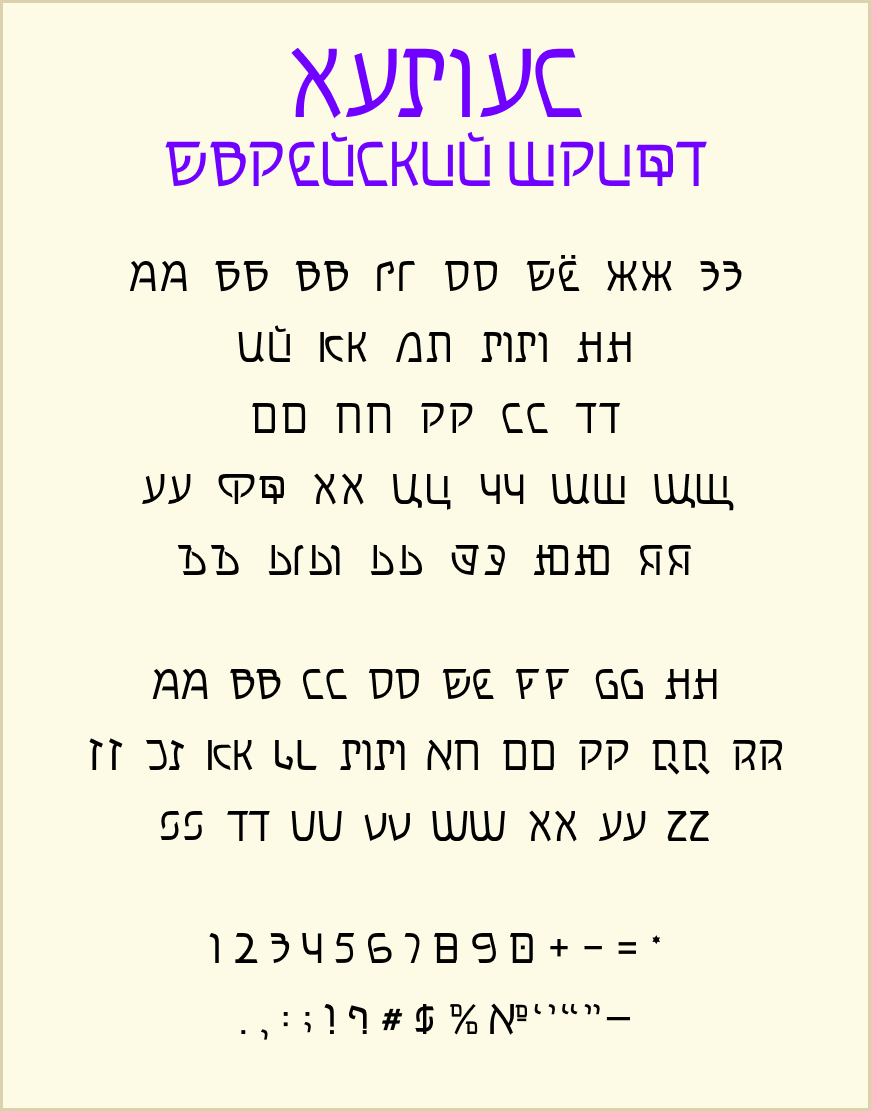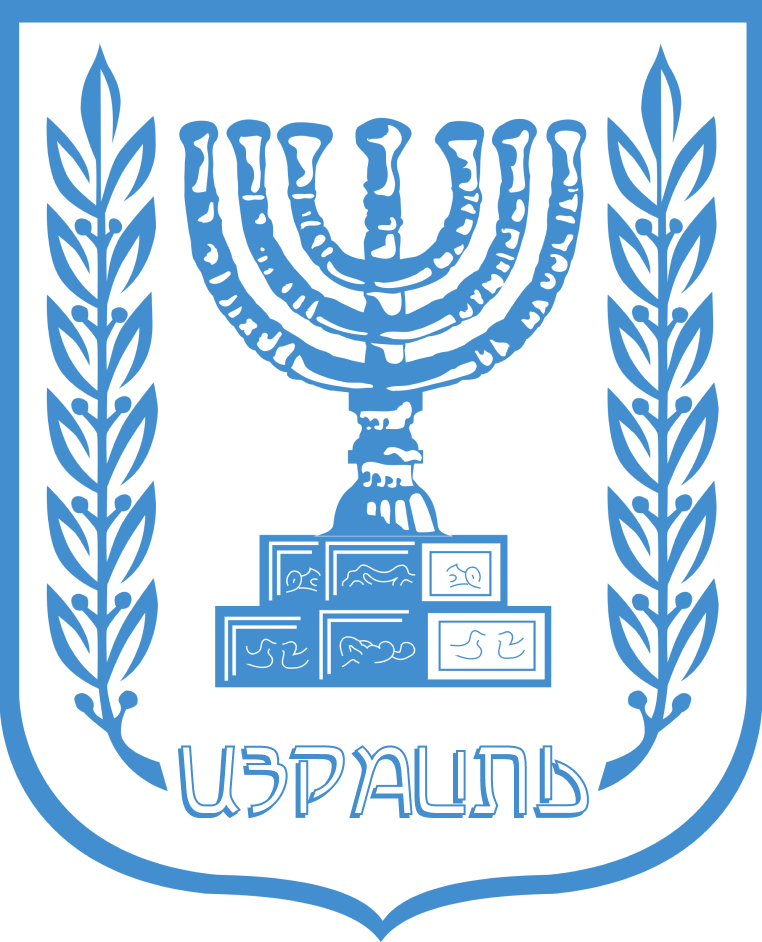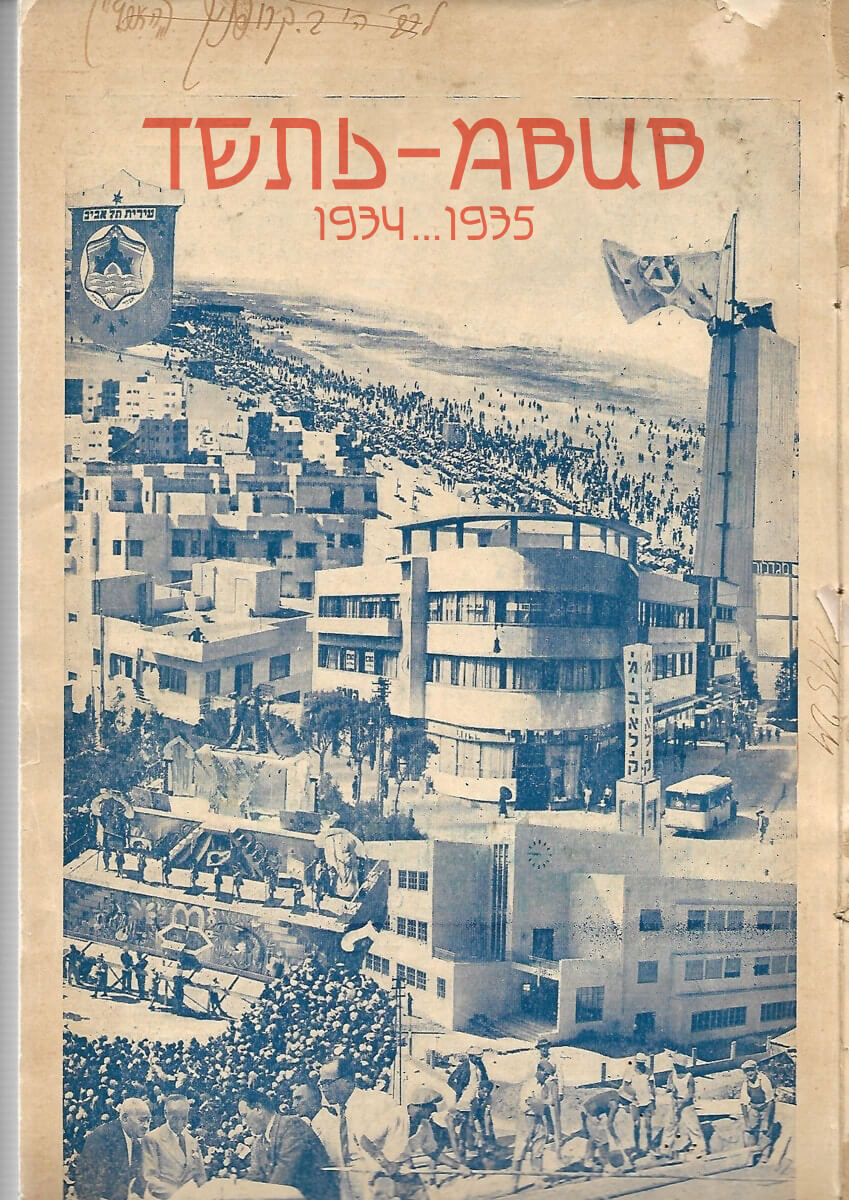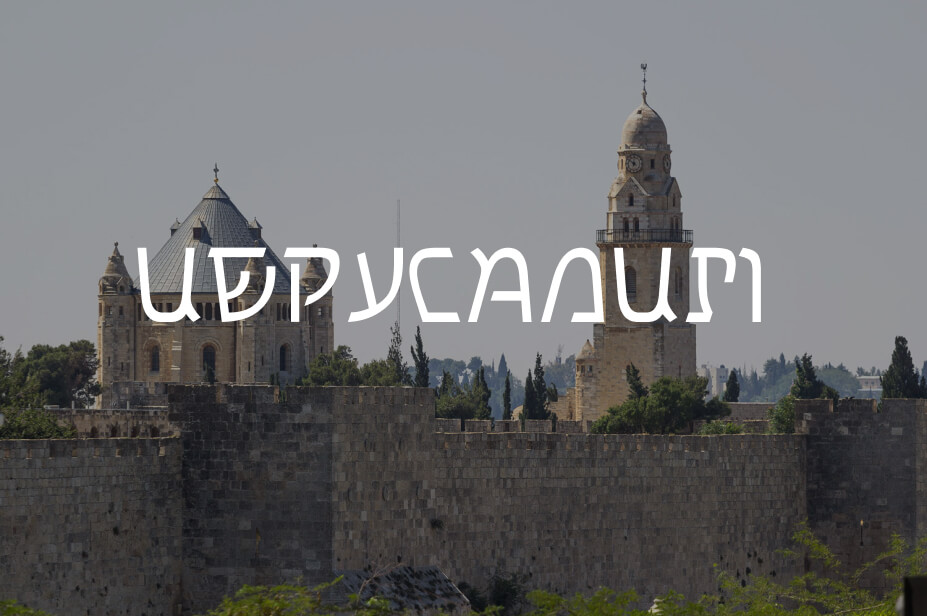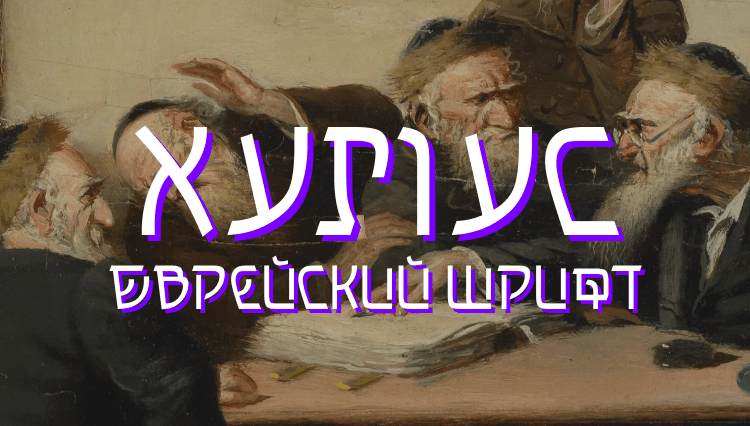
Шрифт в еврейском стиле Хумус
Хумус — кириллический шрифт, выполненный в стиле букв еврейского алфавита. Шрифт включает буквы латинского и кириллического алфавита, цифры и некоторые специальные символы.
Большинство стилизаций под еврейский алфавит выполнены в рукописном стиле, в котором буквы написаны кисточкой и напоминают языки пламени.
Действительно, такие надписи, которые называются шрифтом Раши и были созданы для комментирования Библии, еще можно встретить на уличных табличках в Иерусалиме. Но это декорация, сейчас так не пишут.
Современный наборный иврит выглядит совершенно иначе. Это самое квадратное письмо из всех. Человек, не знакомый с алфавитом, едва отличает буквы между собой. Символы плавные, засечек мало, размеры всех букв примерно одинаковые и вписываются в квадрат.
Поскольку стилизаций под библейский иврит множество, шрифт Хумус подражает современному ивриту. За основу взяты еврейские символы шрифта Lucida Grande. Некоторые буквы получились очень похожими.
Хумус подойдет для оформительской работы. Шрифтом можно подписывать открытки, постеры, картины. Должен хорошо лечь на вывеску еврейского ресторана или ювелирного магазина на старом рынке.
Хумусом сделаны немногочисленные надписи в рассказах об Израиле — про Тель-Авив и Иерусалим.
Примеры использования
Иркутский государственный университет. Скульптурная композиция «Звезды не падают, звезды блуждают».